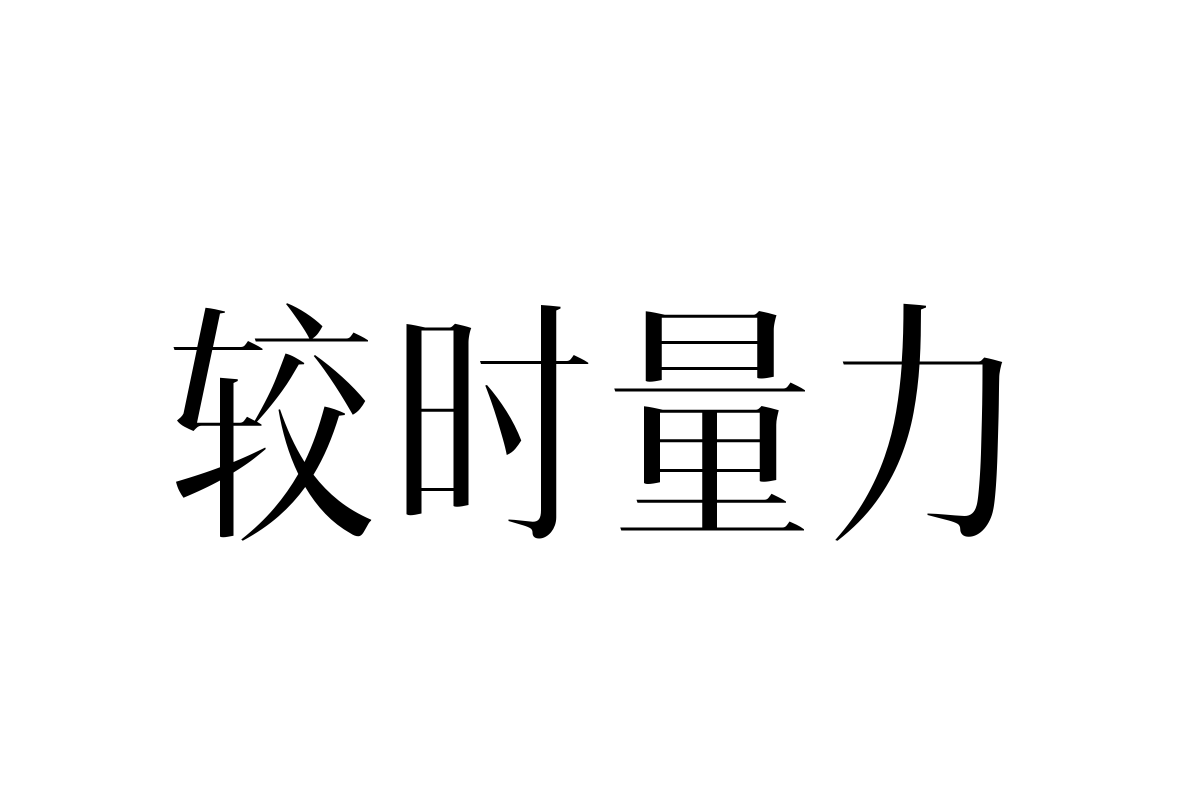
汉仪瑞意宋X45W是一款具有独特设计风格的中文字体。该字体采用现代简洁的设计理念,线条流畅,字形优雅,适用于各类商业、广告、设计等领域。
字体特点:
1. 线条流畅:汉仪瑞意宋X45W的线条清晰,没有多余的装饰,给人一种简洁明快的感觉。
2. 字形优雅:每个字的笔画都经过精心雕琢,使得整体字形显得优雅大方。
3. 适用范围广:该字体适用于各种类型的文本,如标题、正文、广告等,具有较高的通用性。
4. 兼容性好:汉仪瑞意宋X45W具有良好的兼容性,可以在各种操作系统和设备上正常使用。
应用场景:
1. 商业广告:用于制作各类商业广告,如海报、宣传册、产品包装等,能够吸引消费者的注意力。
2. 网站设计:用于网站标题、正文、按钮等文字,提升网站的视觉效果。
3. 印刷出版:用于书籍、杂志、报纸等印刷品的文字排版,提高阅读体验。
4. 产品设计:用于产品设计中的标识、文字说明等,增强产品的品牌形象。